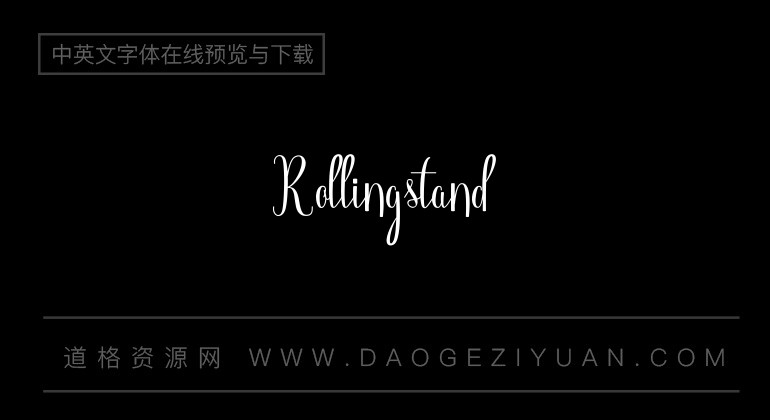
Rollingstand
Rollingstand 是一款现代化的圆滑字体,它的设计灵感来源于手写字体和笔迹,具有美感和可读性。Rollingstand 字体系列由三种不同的字重组成:常规、粗体和黑体,每种字重都包含大写字母、小写字母、数字和标点符号。 Rollingstand 字体采用了现代化的设计风格,给人以简洁、清新、自然的感受,特别适合用于网页设计、印刷和广告设计等场合。同时,Rollingstand 字体的光滑圆润线条,也让它成为一种较为适合于长篇文本排版的字体。 总之,Rollingstand 字体不仅具有美感,而且可读性也很高,是一款值得尝试的字体。
Rollingstand是一款非常不错的手写艺术字体,具有很好的视觉感,适合于文化类的宣传设计、商业类品牌的广告和产品包装设计以及个性化文字排版等较多场景。